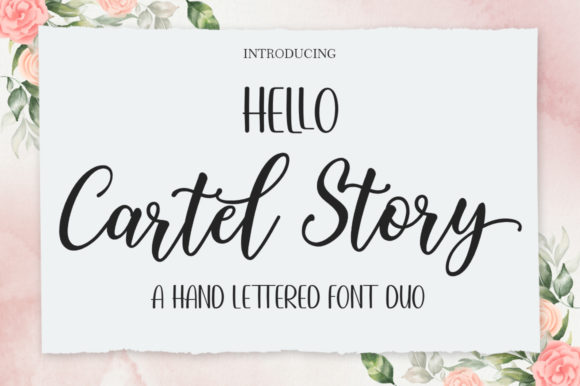
Hello Cartel Story
適切なデザイン要素を見つけるのは難しい場合がありますが、Hello Cartel Storyは作品を即座に引き立てる優れたコレクションを提供します。
POD(オンデマンド印刷)製品、結婚式の招待状、またはソーシャルメディアのグラフィックを作成している場合でも、Hello Cartel Storyは理想的です。